你打开手机淘宝,精美的海报让你目不转睛,你下了单,从快递员手中接过商品,心满意足的那一刻,你不会想到自己在掏钱买下商品的同时也为海报买了单,从模特、摄影到设计师的后期处理,越精美的海报成本越高,当然,你更想不到的是,海报上的每一个字都是要花钱的……
最近,阿里巴巴悄悄推出了全球首个人工智能中文字库,这款阿里汉仪智能黑体测试版,目前拥有3500个中文汉字,将免费提供给阿里用户使用。
这既是阿里给电商卖家的春节福利,也是一种新的尝试,阿里希望用技术手段,降低造字成本,让字体市场进入良性发展。而这项技术的受惠者,除了商家、字体公司,当然还包括了消费者。
一套版权费20万的字体
一套正版字体价值不菲。
据悉,天猫上某商家就为一套方正兰亭字体支付了20万元左右的版权费,虽然14款不同字体可以使用5年,但对商家来讲,“要价还是偏高”。
万一有适合广告宣传的收费字体,但前期没有购买版权怎么办?
让设计师对已有的字体进行修改加工,变成新的字体,是一种解决办法。然而一位设计师曾花了半天时间,只设计出6个中文汉字。
“修改设计每个单字不难,把控字体的统一性才是最难的。”该设计师表示,例如“品”“门”“口”这样的字结构过于单一,在修改时反而会增加难度。“有时会发现,组合成的一句话中出现了两种字体,甚至6个字的标题中会出现6种字体,很头疼。”
出于成本考虑,一些商家并不愿意在购买字体版权上花钱,只使用阿里平台上免费商用的华康字体和开源字体。
还有部分商家,则选择使用未经授权的字体,踩中了涉嫌“字体侵权”的雷区。一旦被字体公司起诉,商家除了赔钱,还要撤回已经发布的字体内容,企业的品牌形象和销售业绩都会受到影响。
为什么造字成本这么高
一套字体为何要价万元,字体公司为何四处维权打官司?侵权与维权的背后,不仅仅是利益的撕扯,还有关于创意价值的认可度。
用传统的方法创造一套字体,其实成本很高,因为需要经过创意、选字、确定、拼字、自动分装等一系列漫长的流程。
一套字体通常有两个特点:字型和字量。字型是设计师对字体的“创意”,字库字体讲究整体的搭配协调和美感。
而每套字体的字量通常由市场需求决定。常用的中文简体有6763个中文汉字,包含中文简繁的9169个,用于出版物的大字符集(包含很多生僻字)27533个,包含稀有地名人名用字的超大字符集包含中文7万字以上。
传统字体公司的设计师,可以设计出很独特的单个中文字体,但即便是难度相对低的字型,他们也很难独立完成整套设计。通常是,主创意者创作五六百个字,确定字体的基调后,再由团队其他成员完成剩下的工作。
每一个字都要经过设计师一笔一画地仔细勾勒、调整。通常,设计一套风格字库需要设计1万个左右的字符和标点符号,少则半年、多则好几年才能进入市场。而且,设计出的字体还可能因为不受用户欢迎而宣告失败。
设计成本居高不下,导致正版字体价值不菲,而正版支持者越少,造字成本越高,价格更加降不下来,造字市场就会陷入恶性循环。
怎么用人工智能造字
阿里巴巴每年也要向字体公司支付金额可观的版权费用,就像阿里人机自然交互实验室经常与字体打交道,因为他们的一个研究方向就是设计智能。
“字体相当于设计领域的水电煤。”实验室负责人杨昌源说,“有的字体真的很好看,我们真的很想用,但是太贵了。”
正版字体这么贵,有没有可能让造字成本变低?杨昌源决定带领团队在字体领域做一个新的尝试,用AI生成字体。
“阿里有人才有技术有资源来做这件事情。”杨昌源觉得,造出一款免费字体,对阿里来讲很有价值,既能让商家不再担心版权问题,也能让字体市场变得更加健康。
彼时,实验室正好与阿里PAI团队在其他业务上有所交集,后者主要负责基于阿里云分布式计算引擎的一款机器学习算法平台,“能不能提供技术支持我们做些事?”杨昌源向对方发出了合作邀请。
实验室想要引入新的技术改变现状,PAI团队想要试验新的技术,双方一拍即合,很快达成跨团队合作的意向,他们打算让机器做出一套“跟人做的一模一样的”精美的字体。
此次AI造字,PAI团队的人工智能专家张庆、孙东慧针对字体生成的特定场景将对抗生成网络(GAN)进行了改进。
团队先用天猫字体和淘字体做尝试,但由于两类字体的样本量太少,在手动补充字体样本,用了一两百组算法模型后,设计团队仍认为,字体的精准度不够,还是半成品。
“因为做精准设计的设计师拥有像素级的眼睛,左偏了一个像素都不舒服。” 杨昌源解释道。
两个团队在标准上不能达成一致,AI造字陷入瓶颈。
造一套自带流量的字
调整方向还是就此放弃?杨昌源决定,引入专业的字体公司一起来制定标准。
找字体公司合作并非一帆风顺。“起初谈的时候蛮难的,字体公司的危机感比我们强很多。”杨昌源表示。
很多人惧怕人工智能技术。最初,字体公司担心,自己的生意甚至是整个字体行业会“没了”,更担心阿里这个巨头会不会进入字体这个商业航道。
“字体并不在阿里的主航道上,我们没有野心深度介入字体行业。”杨昌源反复向对方解释,用人工智能造字,是想要尝试将新技术运用到传统的字体领域,“我们不会跟传统行业直接去竞争,我们更多是给大家一个示范,毕竟专业领域的事情还是要靠专业的人去做。”
在合同上来来回回讨论了个把月后,去年12月,汉仪终于与阿里签订了合同,决定双方联手做一套有AI技术成分的字体。双方决定合作的字体是汉仪公司的明星产品,AI造的字体相当于是给这个系列产品做了延伸。
杨昌源说,“签下合同后,我们定下目标:农历年前,一定要出一个版本给大家看,看能到什么程度。
这次合作中,汉仪字库的设计师负责字体的造型设计,阿里的技术团队负责技术,最终通过“喂养”机器,让其自学并生成了一套字库。
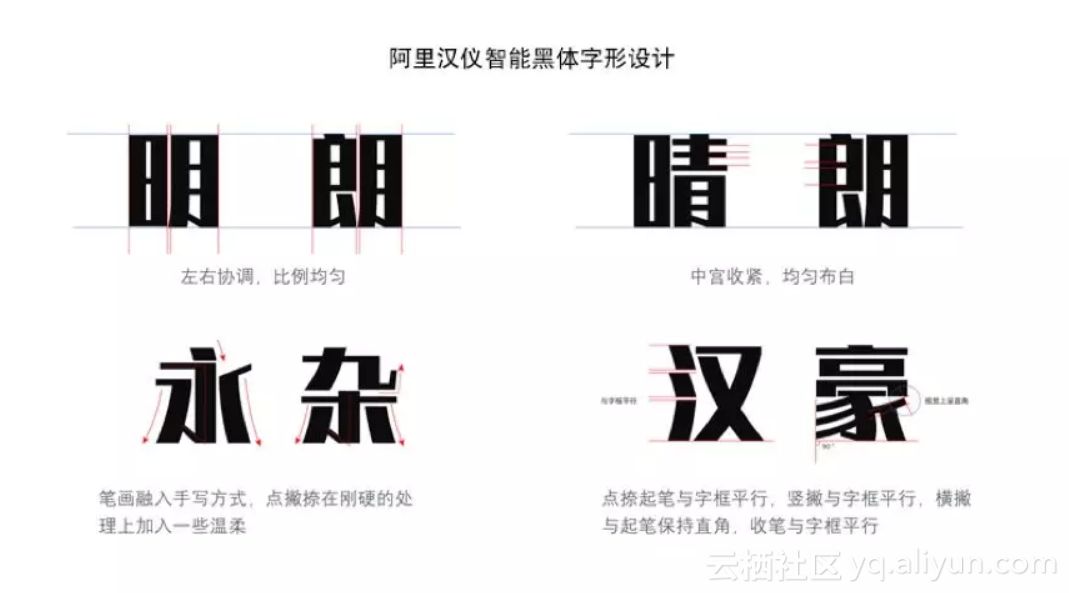
阿里汉仪智能黑体字形设计
在大数据的帮助下,汉仪字库设计部负责人郑乃玉了解到,一套字体设计出约3500字就能覆盖常用的电商广告用语。
让字体设计师们纠结的是,什么样的字体能帮助电商提升销量。他们希望造出一套“自带流量”的字体,郑乃玉说,“例如,商品广告中‘降价了’这样突出的语言最适合使用现在的字体。”
“不能以人为标准去评判AI字体的好坏。”杨昌源表示,评价字体好坏的标准是,生成的字体跟样本字体有90%以上的神似即可,“至少看上去,它像一套字体。”
2018年1月22日,阿里巴巴终于推出了全球首个人工智能中文字库——阿里汉仪智能黑体,并免费提供给阿里用户使用。
正式版将于4月推出
在这套智能字库测试版本发布当天,景德镇胡图网络科技公司的设计师们在第一时间就下载使用了,设计部的胡经理解释,他们的设计师主要做电商设计的排版,自己根本没有时间设计字体,“现在又有新的选择,还是AI生成的,当然要马上试用一下。”
试用后,胡经理也发现了测试版的一些问题,例如螺蛳粉中的“蛳”、聚会中的“聚”字在被放大后会显得棱角不明,像是没有切割完整。另外,阿里这套字体只适用于醒目的大标题,8号、12号大小的字体就不够清晰且略显粗糙。
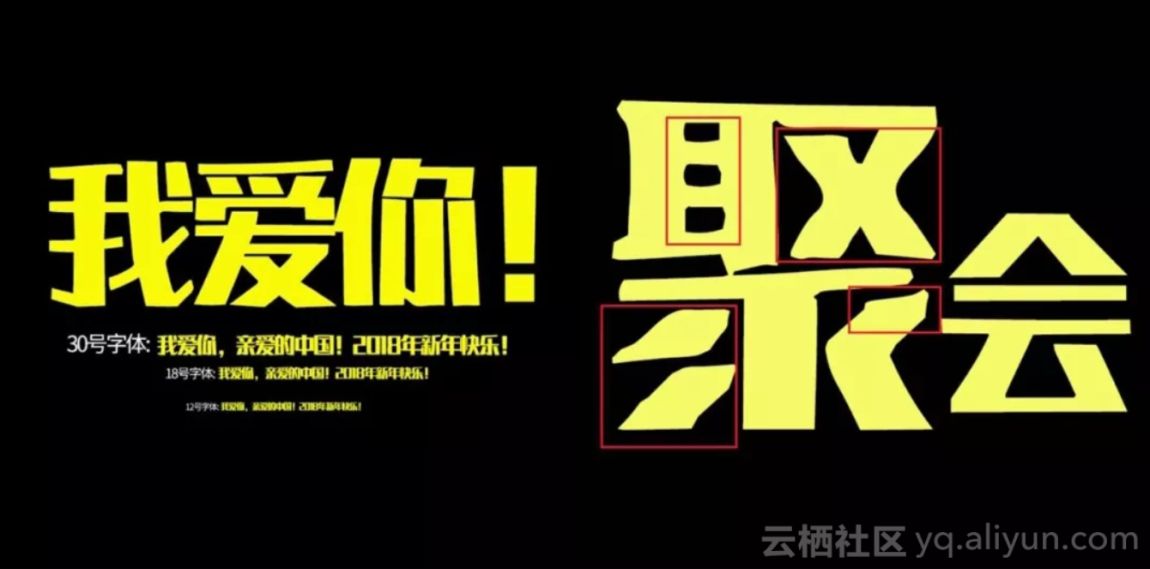
胡经理发现测试版中字体的一些问题
汉仪字库设计部负责人郑乃玉表示,AI只能生成字体,并不会自己做调整,人机协作是目前的最佳手段,“横平竖直、棱角分明的汉字还是要靠人工干预。”
杨昌源也坦言,测试版本不完美,还在继续优化。2018年4月,“阿里汉仪智能黑体”将推出正式版本,最终字符集可能是6763,未来将用于服务阿里新零售下千万商家及阿里设计生态。
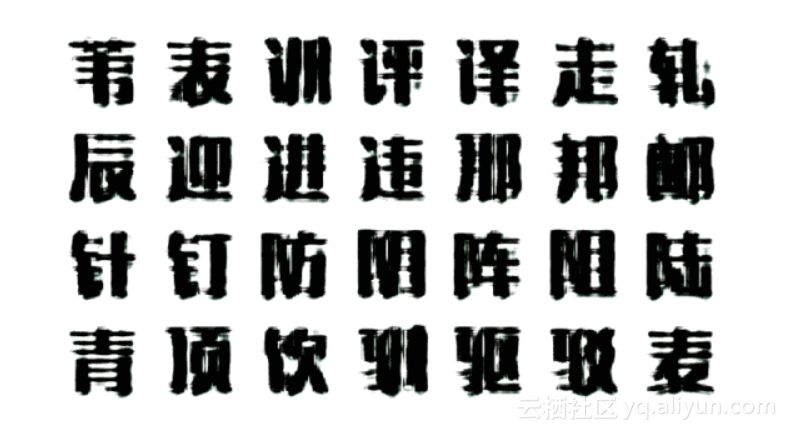
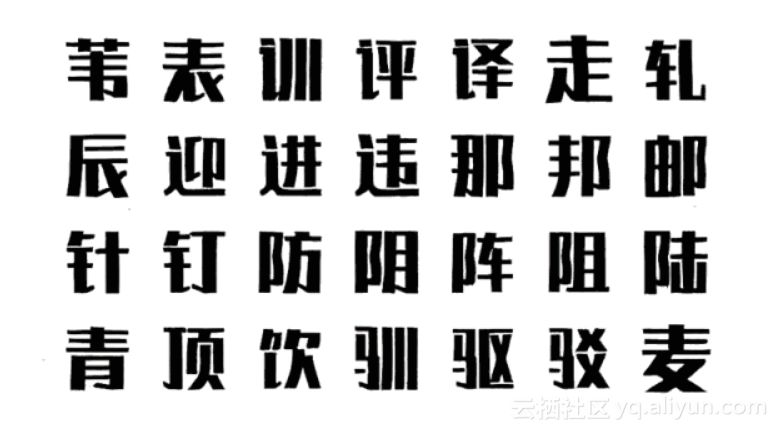
字体机器生成过程
人工智能改变字体行业
电商卖家成千上万,消费者喜欢的风格也五花八门,胡经理就发现,女性用户更喜欢秀气的字体,但这套人工智能字库的字体略显粗犷。
对此,杨昌源表示,“阿里在字体领域做尝试是想告诉大家,字体领域是可以有这样一个成果的,进而鼓励大家在有奔头的情况下去做一些尝试。”
“我们想解决的是,当创意很好的时候,怎么加速创意产生到生成的过程。以前设计一套字体需要投入10个人做一年,现在引进新技术,能够节省4-8个月的时间,可以让字体设计人员把注意力更多的放在创意上。” 杨昌源表示。
按照杨昌源的想象,未来,字体行业可能是另一个景象。“字体生态丰富起来,字体的版权也许就不会那么贵了。”
AI造字的过程中,也产生了副产品。“字体检测,我们能够做的很精准了。” 杨昌源透露,现在他们可以检测某字体可能盗用了哪几款正版字体,并提供相应的概率。
在造“阿里汉仪智能黑体”的同时,团队从市面上收集来雍正的毛笔字,临摹出来后给机器学习,机器通过自学仿造出了雍正字体。这项技术无疑将给字体行业、文物及博物馆修复带来一些新的尝试和可能性。
杨昌源开玩笑说,“以后过年,可以让‘雍正赐字’,给电商卖家做些好彩头视界知产。”